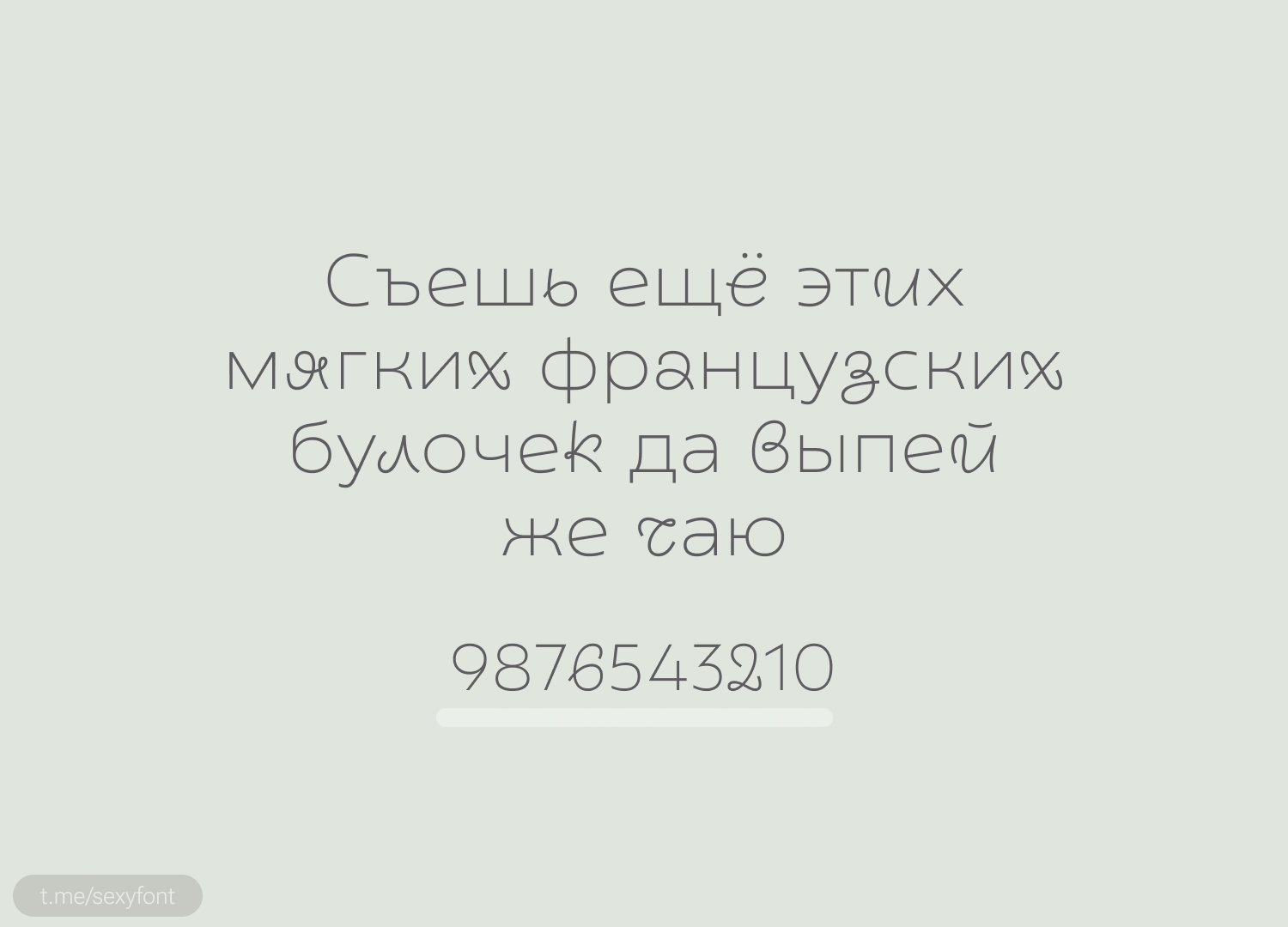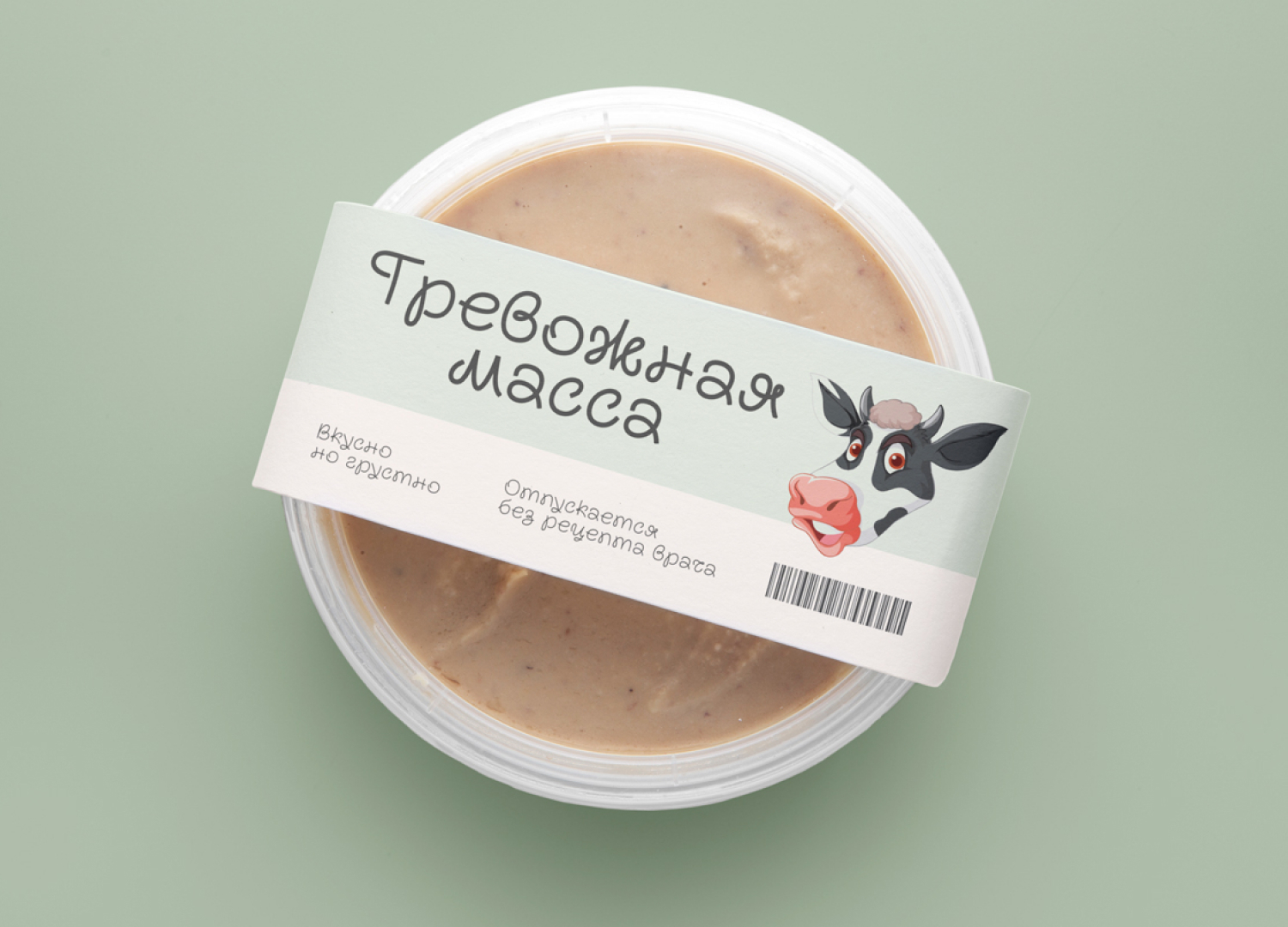
Шрифт Transforma
Декоративный, но при этом вполне читаемый шрифт. Подойдет как для заголовков, так и для небольших абзацев. У шрифта есть несколько начертаний: без декора, с декором у букв и смешанный. Мне понравился последний)